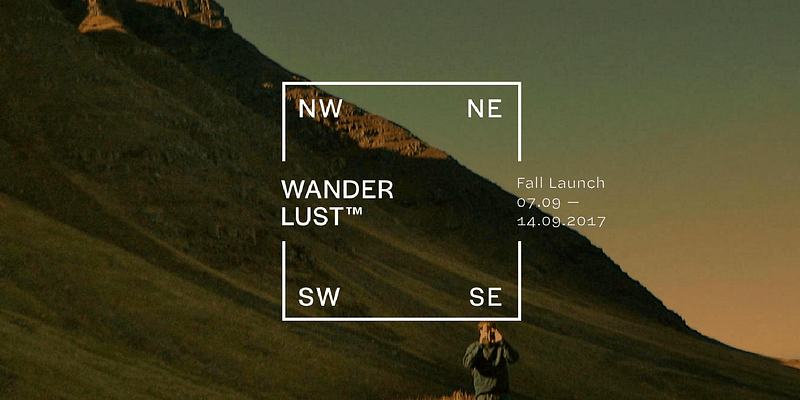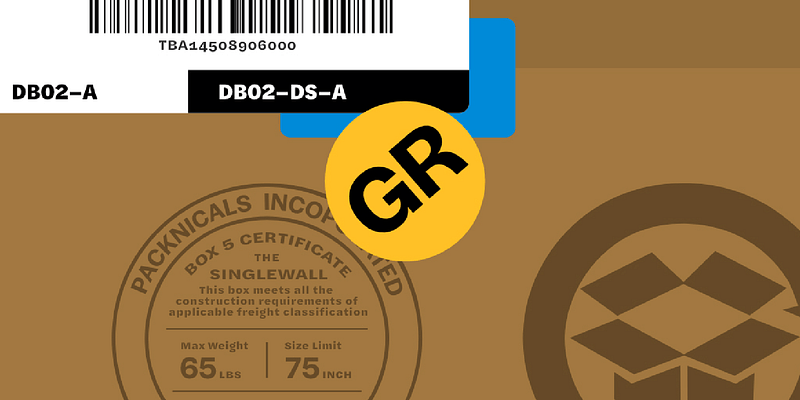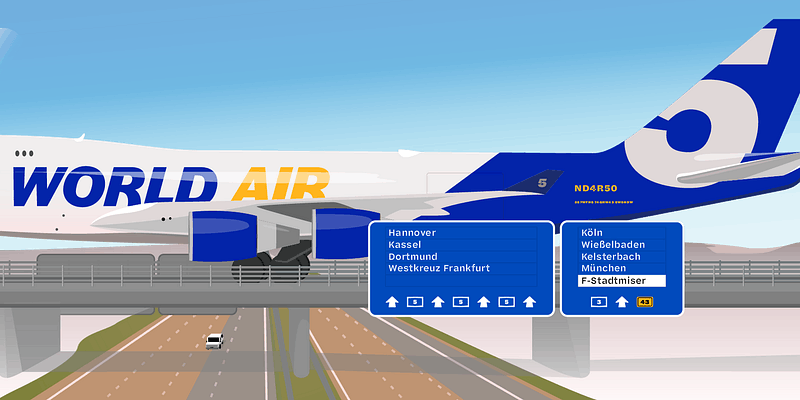
Halyard extiende radicalmente la utilidad tipográfica de la categoría ahora hiperubicua: el Grotesque Sans. La personalidad de Halyard es a la vez familiar y agradablemente distintiva. La superfamilia Halyard muestra la belleza robusta y animada, lista para trabajar en cualquier tamaño. Si bien son muy diferentes en apariencia, las subfamilias ópticas de Halyard funcionan con una personalidad consistente en sus tamaños previstos, creando la impresión de un diseño de un solo tipo.